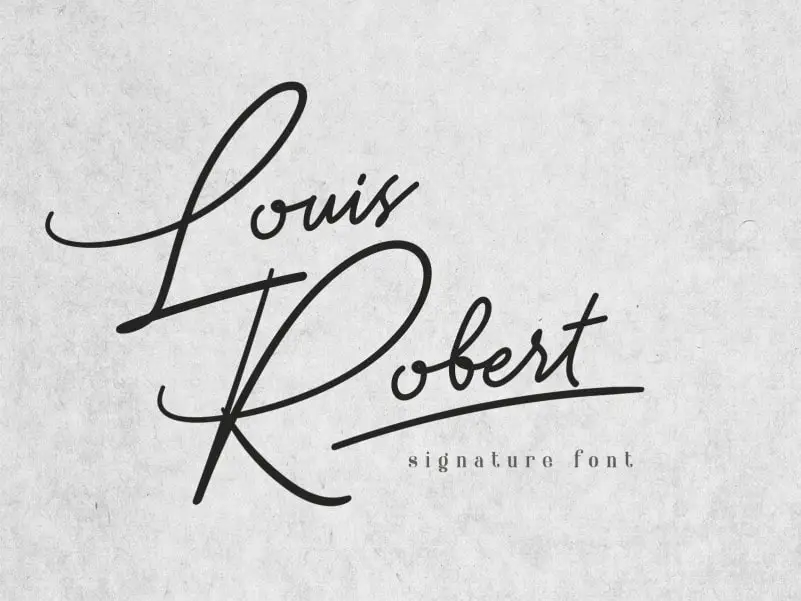
Louis Robert Script Font – Download Grátis
A Louis Robert Script Font é uma elegante tipografia em estilo script que combina sofisticação e simplicidade. Perfeita tanto para criações visuais complexas quanto simples, ela se destaca por seu conjunto de caracteres atraentes e equilibrados. Isso torna-a perfeitamente adaptável a um vasto leque de designs, desde o desenvolvimento de logotipos até a criação de títulos para capas de livros. Nuryanto Dwi, designer desta fonte autêntica, conseguiu criar um design cuidadosamente equilibrado que combina elegância e facilidade de uso. Sem dúvida, Louis Robert Script é uma escolha ótima para quem procura tanto sofisticação quanto flexibilidade na sua tipografia.